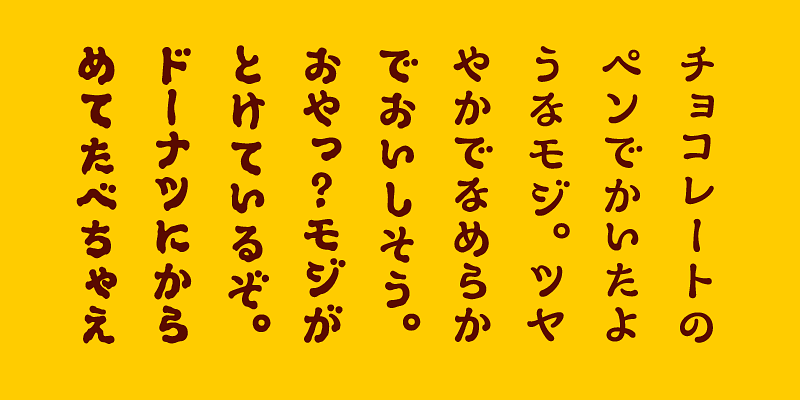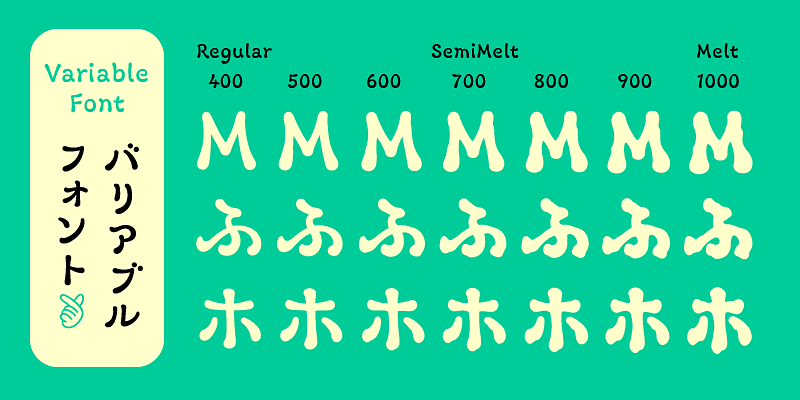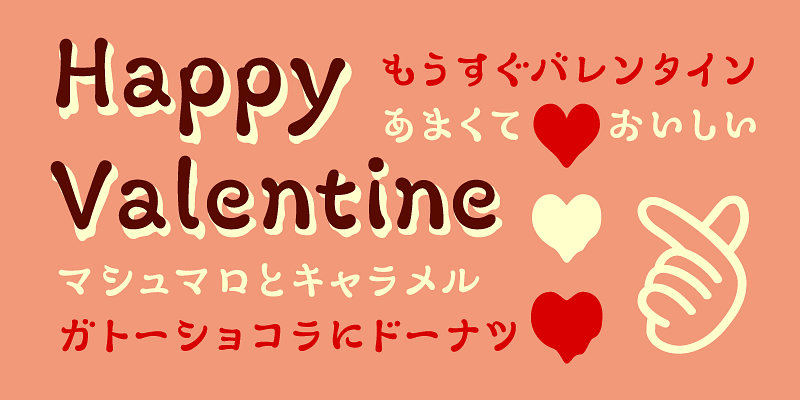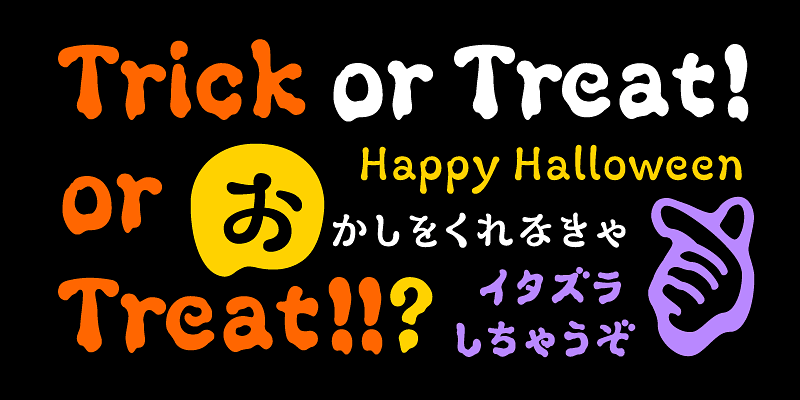
Diese Kana-Schriftart hat eine Form, als wäre sie mit einem Stift aus Schokolade gezeichnet worden. Die Schriftart hat drei Stärken: Regular, SemiMelt und die Buchstaben werden umso dicker, je mehr die Schokolade schmilzt.